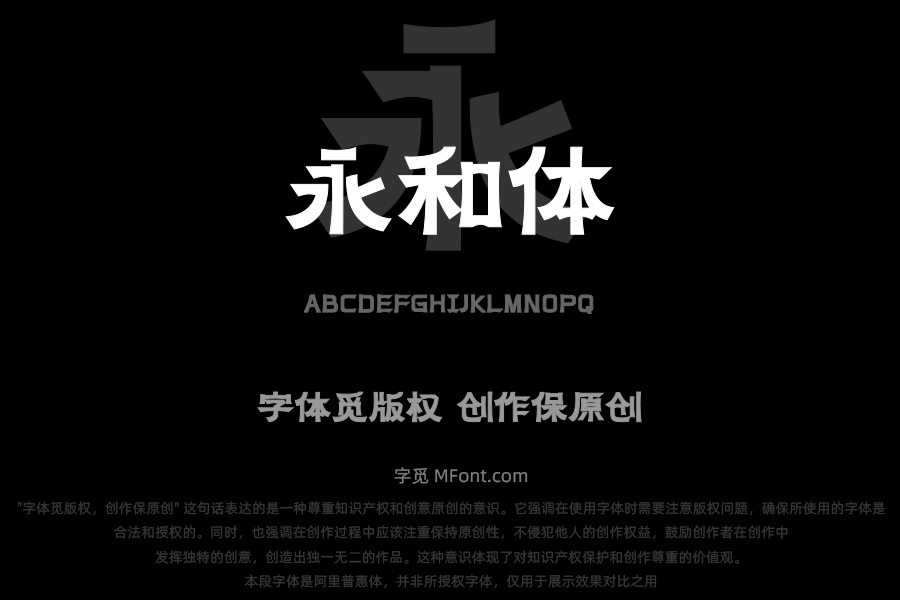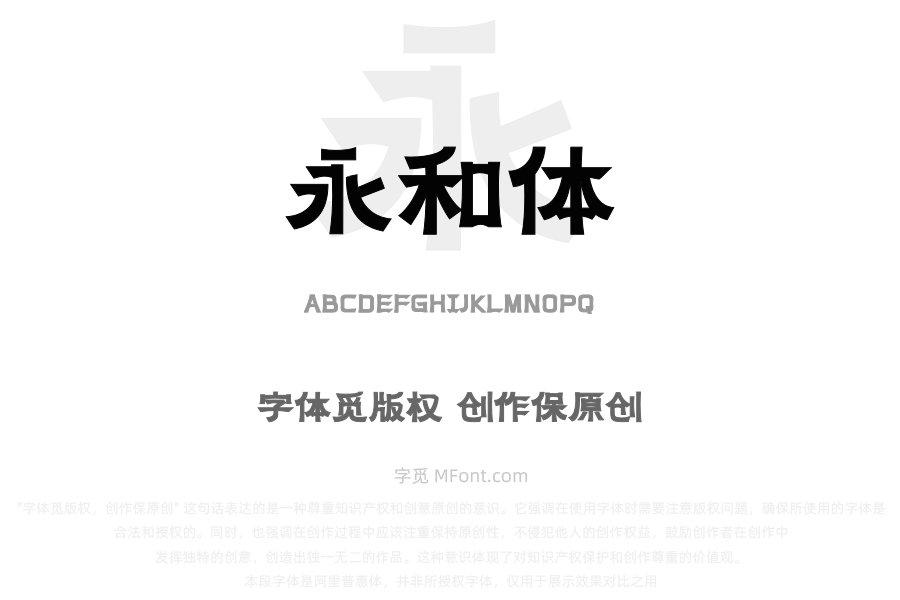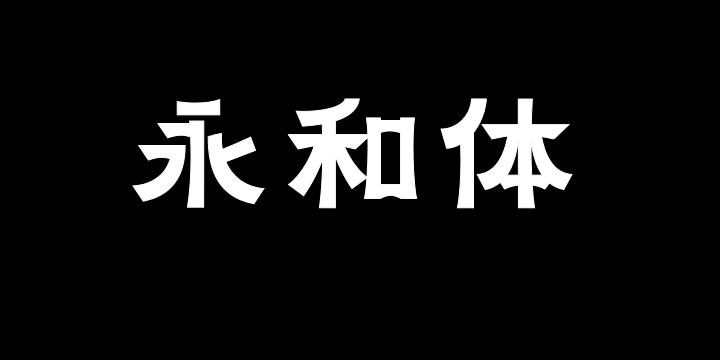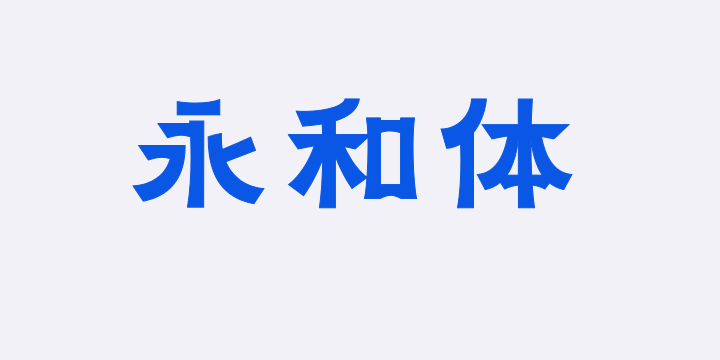
• 上首永和体
字体全名: 上首永和体
字体简介: 上首永和体,简体中文约6763字,在横笔设计上,采用了 “上直下曲” 的独特形态,同时在横笔的两端做尖角处理,让字体在视觉上更具穿透力。竖笔一侧为挺拔的直线,另一侧为流畅的曲线。对一部分竖钩进行简化,横竖连接处将竖笔适当向上延伸,形成突出的视觉效果,使字体更具活力。